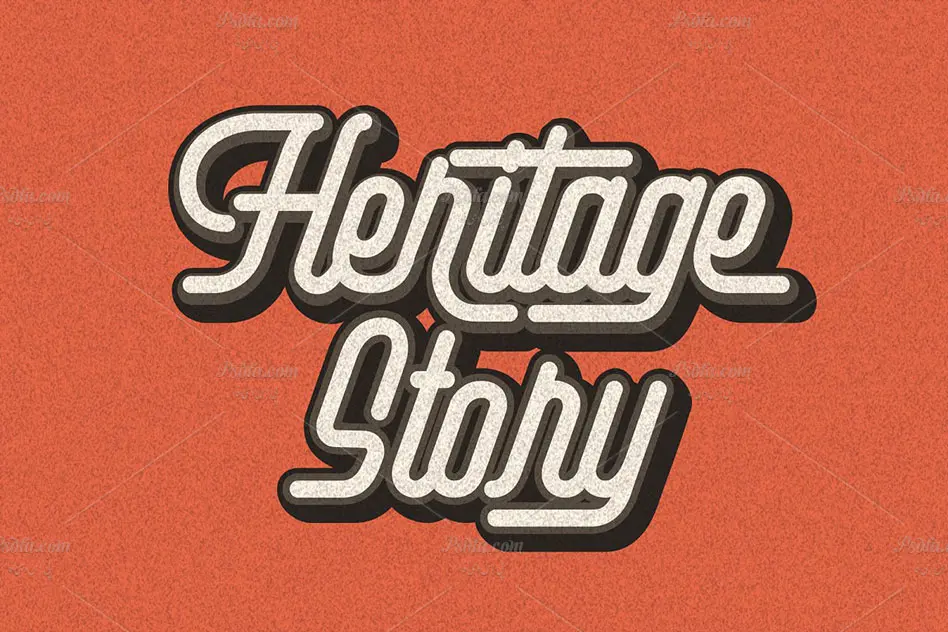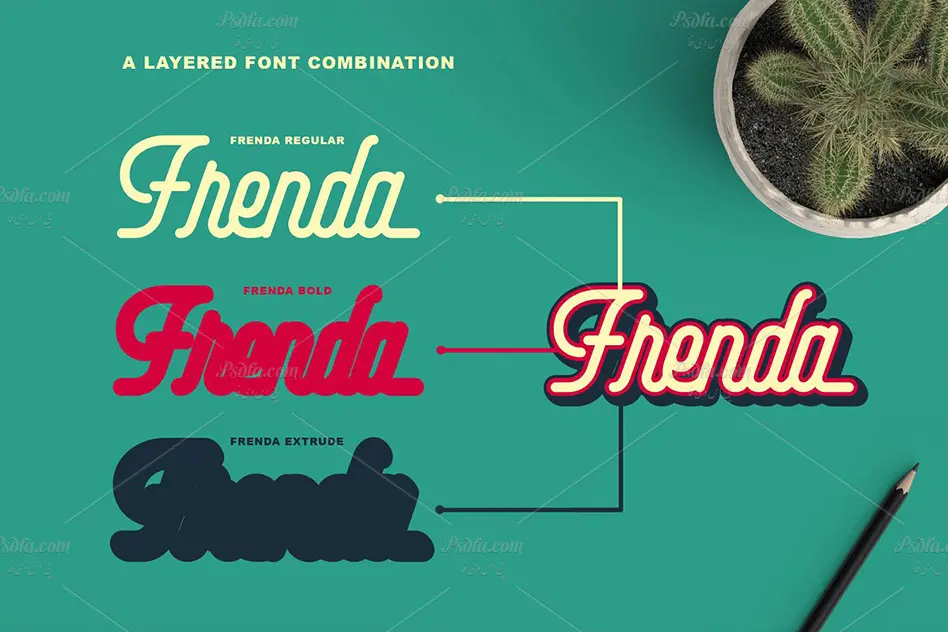
خانواده فونت Frenda مناسب برای طراحی لوگو و پوستر
خانواده فونت Frenda
در این مطلب شاهد خانواده فونت Frenda مناسب جهت استفاده در طراحی و گرافیک به خصوص طراحی انواع لوگو و پوستر می باشید. فونت Frenda در قالب 3 فایل otf بر روی سایت بارگذاری شده اند که با نصب این سه فایل در پوشه فونت های سیستم قادر به استفاده از آن در تمام نرم افزارهای گرافیکی و ویرایشگر متن از جمله نرم افزار فتوشاپ ، افترافکت ، مجموعه نرم افزار آفیس و … خواهید بود. فونت Frenda در سه وزن معمولی (Regular) ، توپر (Bold) و بیرون زده (Extrude) طراحی شده است که می توان از آن در طراحی لوگو ، پوستر ، تراکت ، بروشور ، کارت ویزیت و دیگر طرح های گرافیکی استفاده نمود.